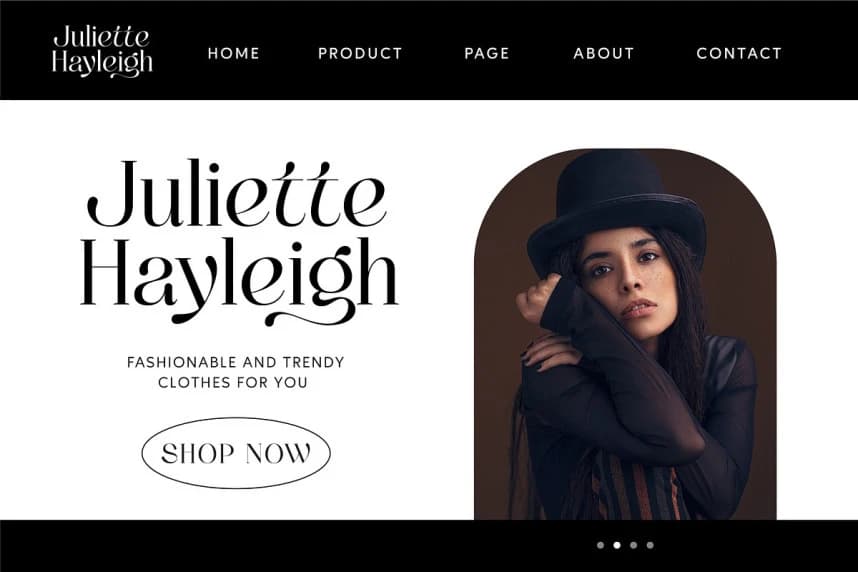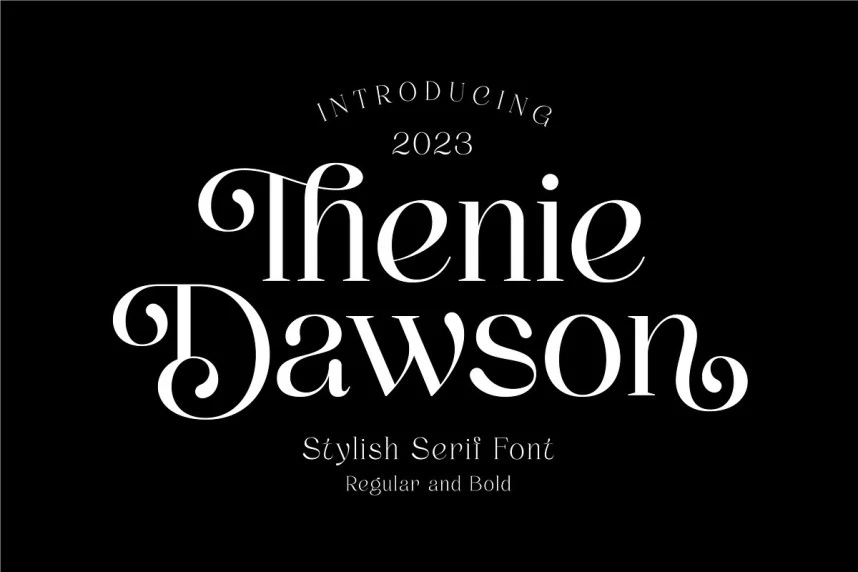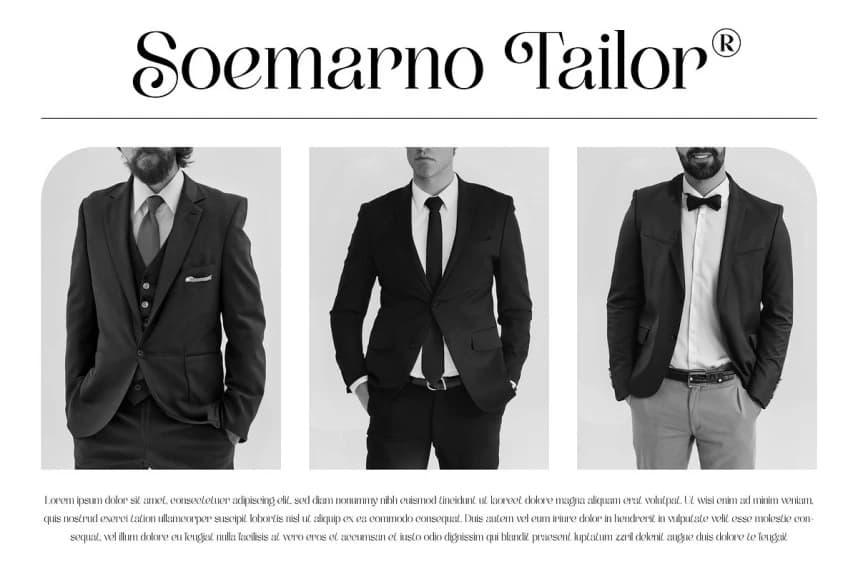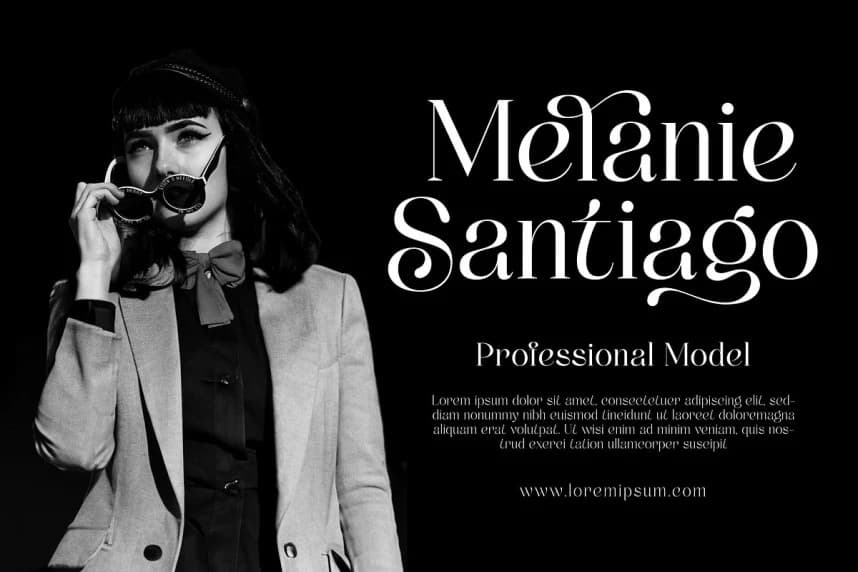
Thenie Dawson Font, zarif ve zamansız bir cazibeye sahip olan şık bir serif yazı tipidir. Bu font, projelerinizin güzelliğini artırmak için tasarlandı. Başlıklar ve alt başlıklar için çok uygun; reklamlar, vintage temalı mood board'lar, markalaşma, logotipler, ambalaj tasarımı ve editoryal tasarım i
Thenie Dawson Font, zarif ve zamansız cazibeye sahip şık bir serif yazı tipidir. Bu yazı tipi, projelerinizin güzelliğini artırmak için tasarlandı. Başlıklar, reklamlar, vintage mood board çalışmaları, marka kimliği, logotipler, ambalaj tasarımı ve editöryal tasarım için çok uygundur.